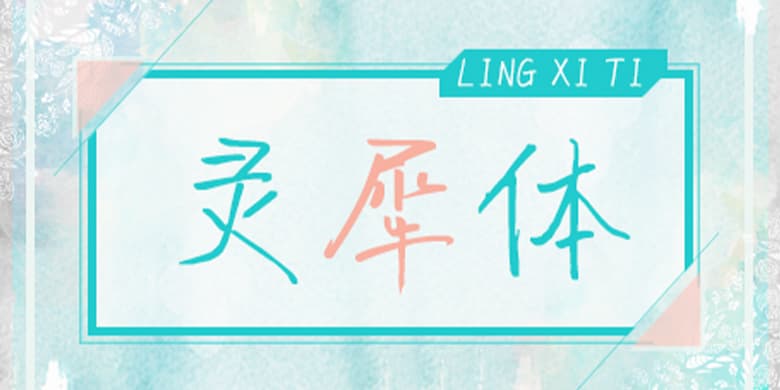
品牌:方正字迹设计师:刘殿儒发行时间:2020字库编码:大陆简体(GB2312-80)分类:常规书写·硬笔字体属性:精品字
该字结构秀美飘逸,洒脱不羁。笔画讲究,具有书法美。灵犀体在气质上颇具侠气,一笔一画似一招一式,侠肝义胆、快意恩仇。适用于文艺类的书刊、品牌广告和产品包装设计,以及社交网络的个性化用字。